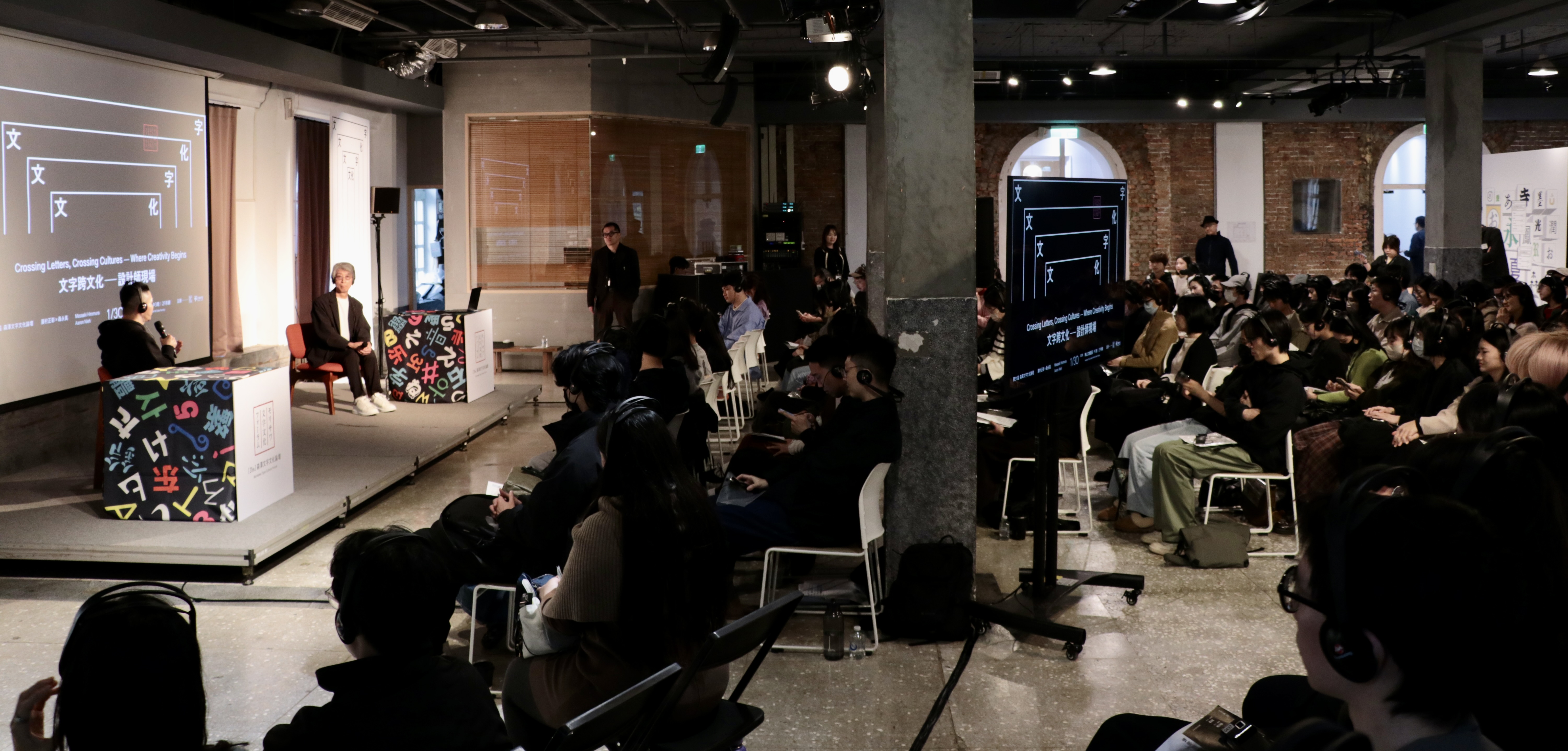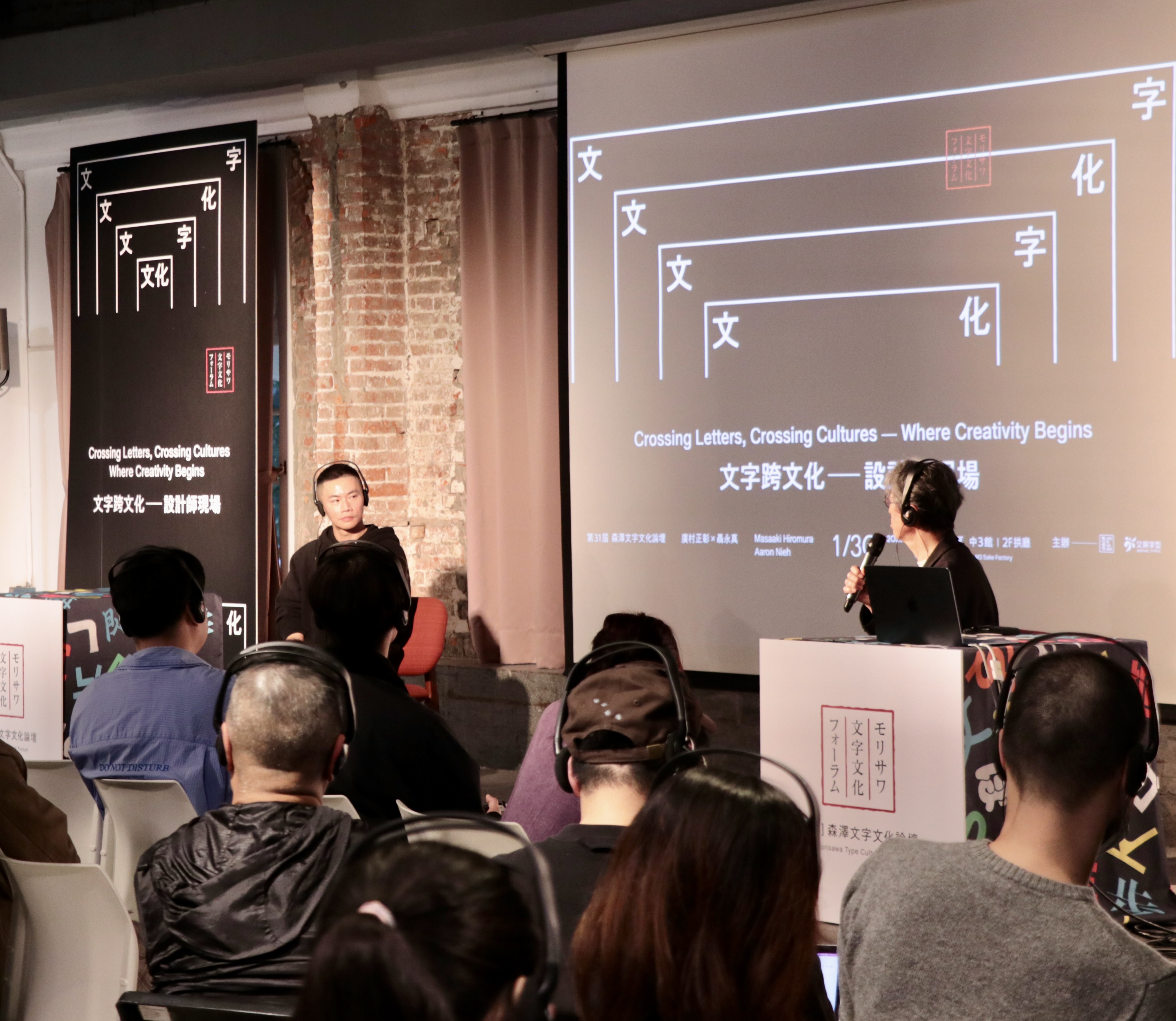
第31回モリサワ文字文化フォーラム「Crossing Letters, Crossing Cultures ― 文字がつなぐ創造のはじまり」
2026年1月30日(金)株式会社モリサワは第31回文字文化フォーラム「Crossing Letters, Crossing Cultures ― 文字がつなぐ創造のはじまり」をArphic Typesと共同開催。会場は台湾の華山1914文化創意産業園区(Huashan 1914 Creative Park)で行われた。
日本と台湾という異なる文化背景の中での廣村正彰氏、Aaron Nieh氏の二人のグラフィックデザイナーが登場。それぞれの実践を通じて「文字の力」を多角的に掘り下げた。
廣村正彰(グラフィックデザイナー )
Aaron Nieh(グラフィックデザイナー )
第1部:Aaron Nieh 氏 講演
Aaron Nieh氏は、今回のフォーラムへの招待に感謝を述べたうえで、本講演では作品紹介に終始するのではなく、自身の思考の出発点や、キャリア初期の視点に立ち返りながら話を進めていき、まだ自身が広く知られる以前(約20年前)の初期作品を振り返り、どこを注視し、どのような条件や目的の中で生まれてきたのかを、来場者と共に考えていきたいと述べた。
比較文学的視点とデザイン
「デザイナーは翻訳者でありインタープリター(解釈者)である」と話し始めた。
文学作品の翻訳を例に挙げ、同じ物語であっても、文化的背景や世代が異なれば内容やニュアンスが変化することを指摘した。Nieh氏は、こうした現象を比較文学の一形態として捉え、デザインもまた同様に文化と言語のあいだを横断する「解釈の行為」であり、デザイナーの重要な仕事は「物事への理解を最も適合する形」にすることだと語った。
文字と文化を横断する実践 ー タイトル翻訳とキービジュアル制作 ー
今回のフォーラムタイトル「Crossing Letters, Crossing Cultures:Where Creativity Begins」について、英語でのやり取りからスタートし、単なる中国語の直訳ではなく、台湾人の持つ言語のリズムに合い魅力的に伝わるよう「越える」「またぐ」といった漢字が持つ意味やイメージを重ね合わせ、「文字を超える文化」という表現に至り、その過程自体が、文字と文化を横断する実践であったと振り返った。
キービジュアルについても、文字の中に文化が含まれ、文化の中に再び文字が内包され、拡張していくイメージを映像的に表現したと説明。同じタイトルであっても、異なるデザイナーが手がければ全く異なるビジュアルに着地する可能性があることに触れ、そこにデザインの本質があると述べた。
文字跨文化 Crossing Letters, Crossing Cultures
日本語の「タイムマシン」は機械的なイメージが強いが、中国語訳の「時光機」は台湾で使われる場合もっとエモーショナルなものを指すという。Nieh氏は、翻訳や通訳を介することで生じる「わずかなズレ」に注目し、それは誤差として扱われがちだが、むしろそのズレを見せることが創造性の源泉になり得るのではないかと指摘する。
20年前、自ら手掛けた日本語を組み込んだデザインや中国語の文脈にひらがなを取り入れた映画や本のタイトルを紹介し、言葉をミックスした表現は新たな解釈や表現を生み出す契機になったとし、それらを振り返り、文化や時代背景で、そのデザインの持つ意味の重心が少しずつ移る。現在はより母国語を大切にしつつ新たな表現を創出していると述べた。
また、台湾のミーム※で展開されている日本語と中国語、アルファベットやカタカナが混ざり合う表現は、特定の文化圏に属する人にだけ通じる一方で、新しいコミュニケーションの形を生み出している。こうした現象は、今後さらに増えていく可能性があり、文字文化も変化し続けるものであるという見解が示された。
講演の終盤、Nieh氏はデザイナーの姿勢について、なぜその表現を選び判断に至ったのかを自覚し、自身の美意識や主張を理解したうえで表現すること、そして自らの選択に対して後ろめたさを感じる必要はない、と締めくくった。
第2部:廣村正彰 氏 講演
続いて廣村正彰氏が登壇。Nieh氏の講演でも話された、台湾での日本語と中国語が組み合わさったデザインや文脈の面白さに触れ、台湾語/中国語にとても興味が湧いたと語った。
字と美について
日常生活の中に溢れる文字やサイン、見過ごされがちな表現を改めて観察することで、文字文化の奥行きや可能性が見えてくる「当たり前のものに立ち止まって目を向ける」ことの重要性を説き、自身はグラフィックデザイナーであると同時に、空間デザインにも多く携わってきた立場から、今回のテーマを「字と美」とした。調和する文字の美しさについて考える場にしたいと述べた。
「読む」文字と、「観る」文字
廣村氏は、人間の脳が文字を読む場合と、絵や形を見る場合で異なる領域を使っていることに触れた。読む文字は主に情報を正確に伝える役割を担い、見る文字は視覚的・感覚的な情報を伝える。特定の文字文化圏=アジアでは文字そのものを美的要素として捉え、字と絵が一体化した表現を育んできた歴史があり、それが書文化を豊かにしたと説明し、文字を「読むもの」としてだけでなく、「観るもの」「空間の中で機能するもの」として捉える視点を提示した。
情報から表現へ ― 文字の分岐点
講演の中盤では、「文字が情報から表現へと2つに分かれる分岐点」について言及した。
「観る字」は記号化されピクトグラムやアイコンのように読まなくても意味が伝わる即時性を持つ文字。
「読む字」は建築の看板やサインなど空間に配置されることで機能し、読むとその空間の意味が伝わる文字。
場所や身体感覚と連動した表現であり、見ることと読むこと、二つのことが同時に行われていると説明した。
象形文字と現代の絵文字
廣村氏は、象形文字や亀甲文字を例に挙げ、古代において文字が視覚的な形から生まれたことを説明。伝えたい情報の本質を、最小限の形で表すという考え方は、現代の絵文字やピクトグラムにも受け継がれている。「ピクトグラム」は、「読む」ことを極限までそぎ落とし、見ただけで意味が通じるように設計された記号である。そのため、意味を直接視覚化するところに面白さがあり、言語や年齢を超えて、情報を共有することが可能であると述べ、一文字で意味を持つ「漢字」の中にイラストと英訳を入れたサインを紹介。商業施設内にある食品フロアやレストラン街の壁面など、幅広い人々が利用する空間に配置することで、全世代、外国人の認識を容易にし、豊かなコミュニケーションを担えるデザインとなり、単なる情報伝達を超えた表現が可能になったと述べた。
文字と空間デザイン
東京2020スポーツピクトグラム、横須賀美術館などのサインやピクトグラムを紹介しながら、「文字は情報を伝えるだけでなく、空間の方向性や距離感、体験そのものをデザインする要素として機能する。配置やスケール、視線の誘導によって、人がその場でどのように感じ、どのように行動するかが変わる」と語った。
空間認識化された字 環境への定着
文字と絵が一体となった表現の例として、山水画と和歌が描き込まれた屏風絵を取り上げ、さらに自らのスタディとして実景に俳句を設えた写真作品を紹介。サインには即時性が重視されがちだが、時間をかけて空間の意図を伝えるサインも存在する。その際、「言葉」や「文字」は、空間を構成する有効なパーツとなり、文字は「読む」ことができるからこそ、絵や形だけでは伝えきれない情報を内包し、それが脳への刺激となり、空間の理解や共感を深めていくと述べた。
こうした視点を踏まえ、言葉と空間が響き合う表現は日本に古くから受け継がれている美意識だと語り、文字は単なる情報伝達の手段ではなく、美や文化、感情とも深く結びついた存在であるとして、講演を締めくくった。
第3部:クロストーク・質疑応答
Aaron Nieh氏と廣村正彰氏が登壇し、「文字は文化の立場であり、スタンスである」というテーマのもと、クロストークが行われた。
廣村氏は、サインデザインについて、単なる補足的でネガティブな存在ではなく、環境に新たな意味や役割を与え、価値を創出するポジティブな行為として捉えるべきだと主張。台湾と日本の違いとして言語や施工面の違いはあるものの、台湾の現場は柔軟に対応してくれる印象があると述べた。また、デザインの役割は「人が理解するためのきっかけをつくること」にあるとし、海外案件では相手国を知り、尊敬し、寄り添う姿勢を重視していると語った。
Nieh氏は、廣村氏の話を受けて「文字」や「観る/読む」といった行為の原点に立ち返りたいと述べた。自身の変化については、若い頃は形式やスタイルにこだわっていたが、今は内容の充実を重視し、個性と最適な表現のバランスを模索しながら、新たな手法への挑戦を前向きに楽しめるようになったと語った。
質疑応答で両者は、サイン計画ではその土地のフォントを用いることが自然だと述べ、デザインの変化については、時代や技術が進化しても本質は変わらず、チームでの共有や外部との協働が重要だとした。AIは最終成果物には用いないが、検証など制作プロセスの一部として活用していると述べた。
お二人の講演から文字は情報として読むだけでなく、文化や空間を映し出す「見る言葉」であり、サインやピクトグラムは単なる案内ではなく、空間の意味や体験を設計する創造的行為であると実感させられた。
翻訳や世代差で生まれる微細なズレから新たな解釈や表現を生むデザインの面白さが伝わり、デザインと言語の関係性、表現の広がりが台湾と日本を跨ぎ「文字の力」を存分に感じる貴重な講演となった。